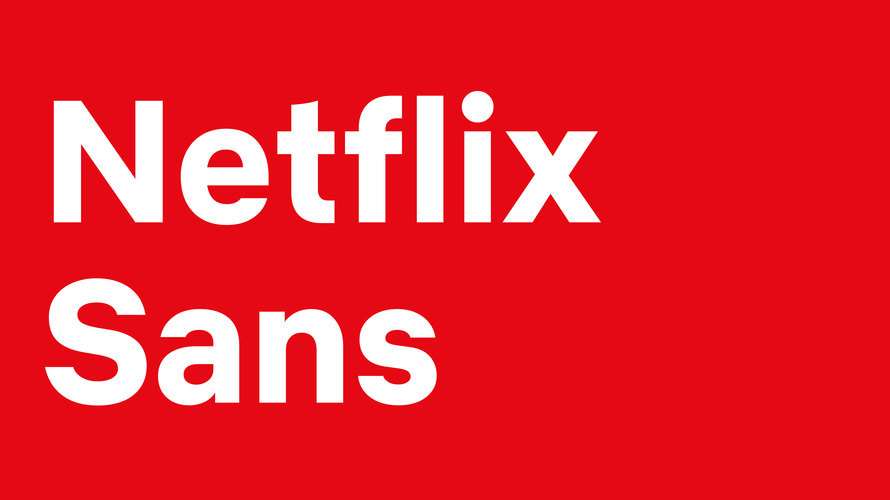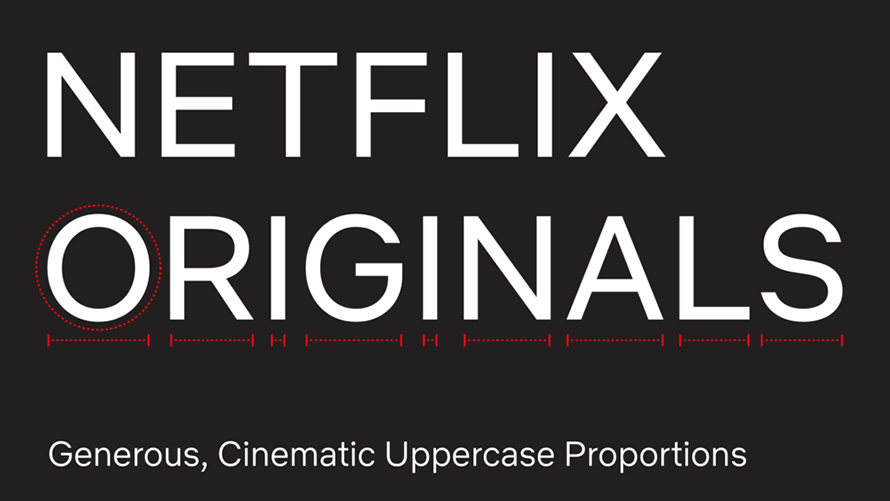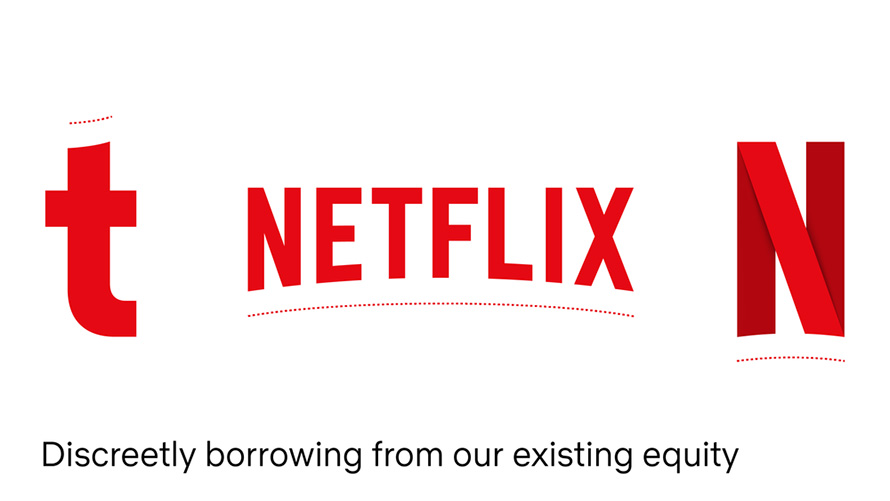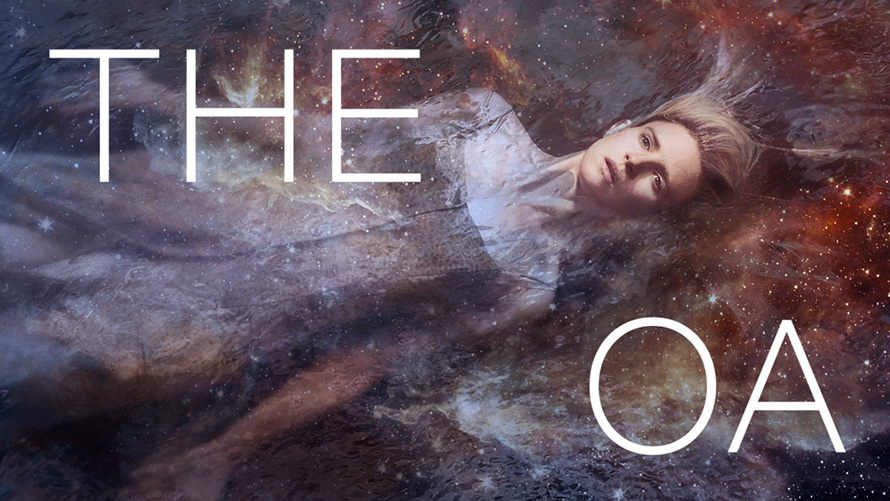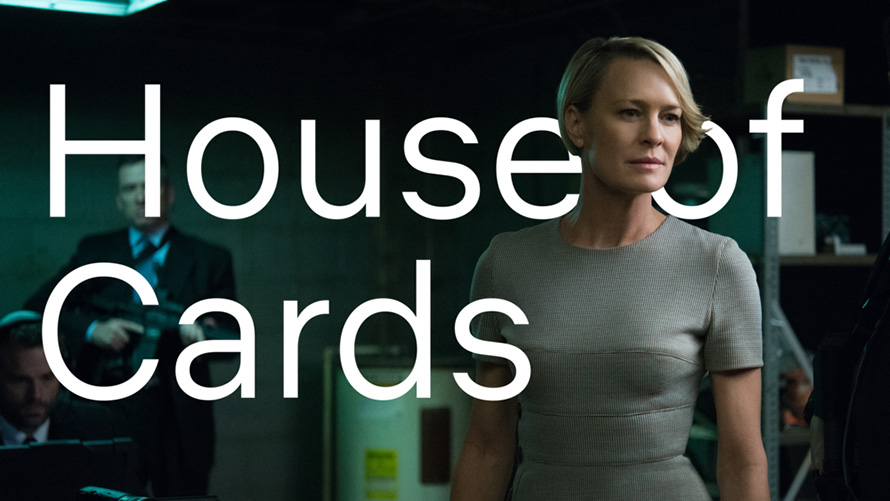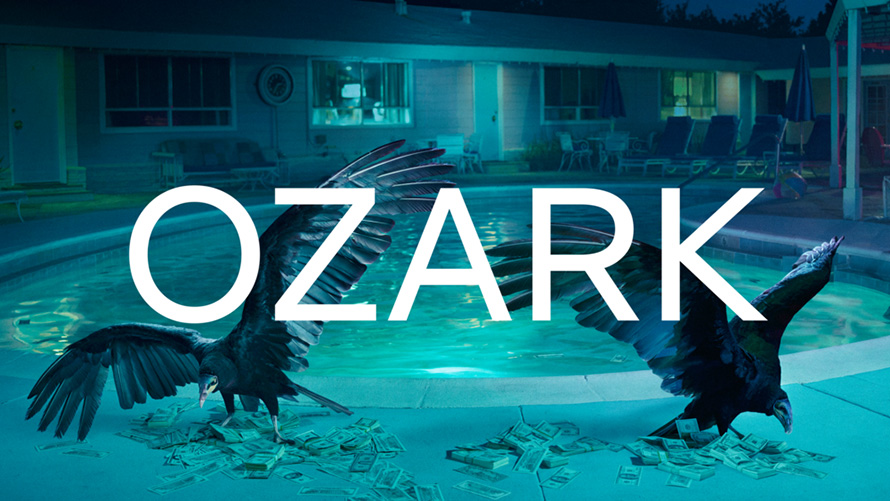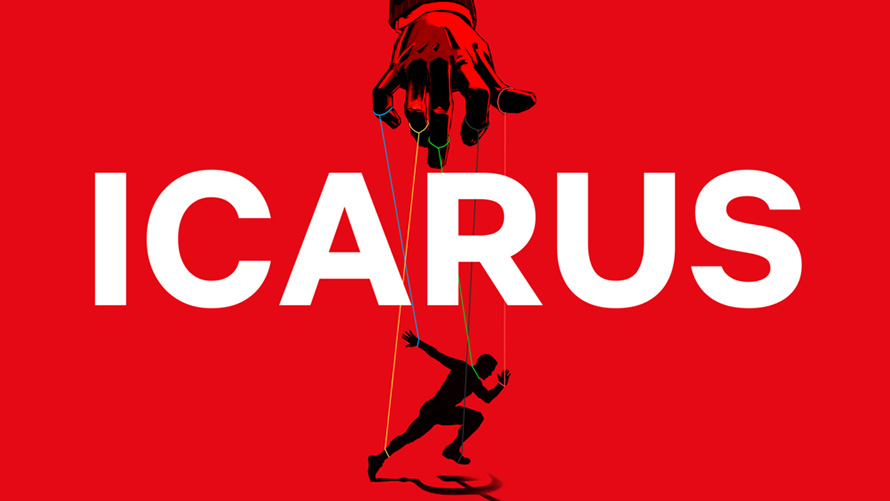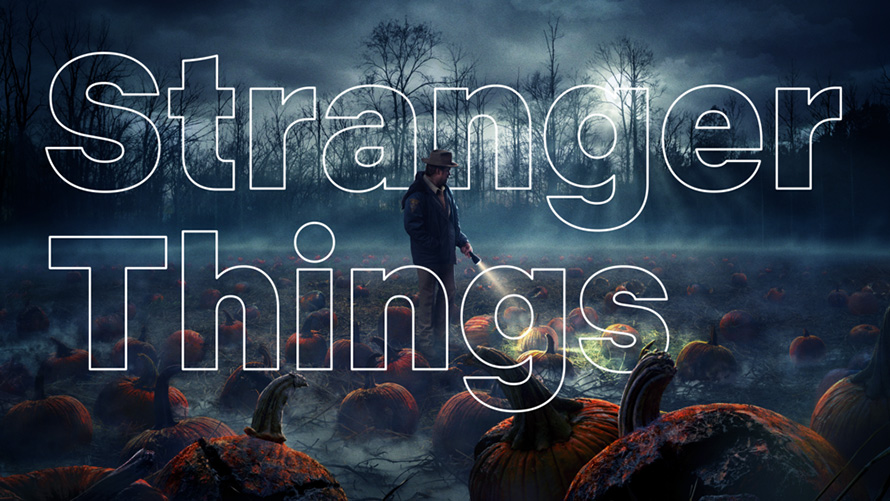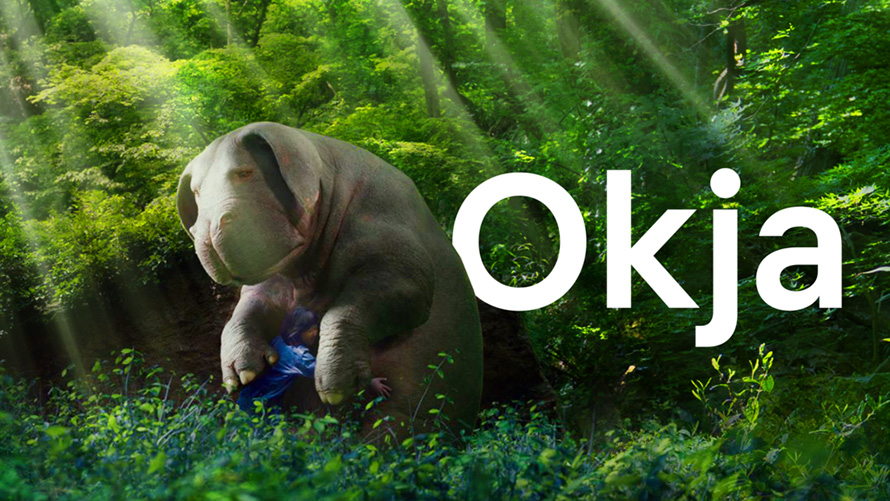
Netflix vừa phát triển bộ phông chữ mới với tên gọi Netflix Sans, với ý định thay thế cho phông Gotham mà họ sử dụng từ trước đến nay.
Có thể nói Netflix chính thức có một phông chữ cho riêng mình giống như Apple, Google, Samsung.. đã làm. Bộ font mới được phát triển theo hướng đơn giản, hữu dụng và tinh tế lấy cảm hứng từ biểu tượng nổi tiếng của thương hiệu này – và đặc biệt quan trọng là tính kinh tế khi mà nó có thể tiết kiệm cho công ty này đến hàng triệu đô mỗi năm.
Một trong những người dẫn đầu dự án, Noah Natham giới thiệu về project này trên trang cá nhân của mình. Anh chia sẻ rằng bộ font Netflix mới có thể đáp ứng tốt cho việc trưng bày, hiển thị và cả về tính năng. Ngoài ra bộ font mới cũng thực sự mang tính kinh tế.
Nathan chia sẻ:
Với một công ty mang tính toàn cầu như Netflix, bản quyền cho font chữ có thể trở nên khá tốn kém. Phát triển kiểu chữ riêng cho mình không chỉ tạo ra một yếu tố độc đáo cho thương hiệu về mặt nhận diện (đưa Netflix ra khỏi Gotham, vốn là một loại font được sử dụng rộng rãi trong ngành giải trí), nhưng cũng tiết kiệm cho công ty hàng triệu đô một năm khi các tác giả bắt đầu chuyển hướng tính giá bản quyền dựa trên mức độ hiển thị trên nhiều kênh quảng cáo số.
Đường cong trên chữ “t” viết thường mang đến một cảm giác thú vị, nhắc đến logo nổi tiếng Netflix (đã được ra mắt cùng với sự ra đời của công ty vào năm 1997 và được chỉnh sửa vào năm 2014), nó được lấy cảm hứng từ logo của CinemaScope – một loại ống kính anamorphic được sử dụng trong những năm 50 và 60 để quay phim màn ảnh rộng.
Cùng xem qua bộ font Netflix Sans qua những hình ảnh dưới đây:
Netflix Sans Thin:
Netflix Sans Light:
Netflix Sans Regular:
Netflix Sans Medium:
Netflix Sans Bold:
Netflix Sans Black: